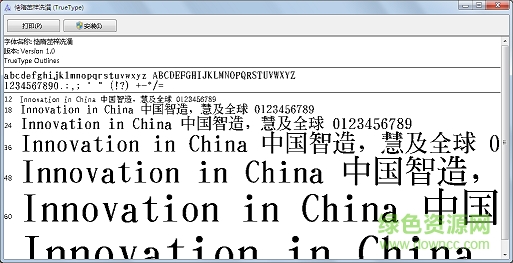
gbinnmingbold
gbinnming bold字體是一款秀美好看的文鼎小標(biāo)宋簡(jiǎn)體,筆畫單純,線條清晰流暢,字形秀氣規(guī)范,可用作正文文本字體!
宋體介紹
宋體是中國(guó)明代木版印刷中出現(xiàn)的字體。最初是在復(fù)刻臨安書棚本時(shí)將筆劃加以直線化,呈現(xiàn)出硬朗表情的一種字體。
嘉靖三十二(1553年)刊刻的《墨子》中宋體的基礎(chǔ)已經(jīng)成型。明朝后期的萬歷年間刊本數(shù)量急速增加,促進(jìn)了書籍制作的分工化。